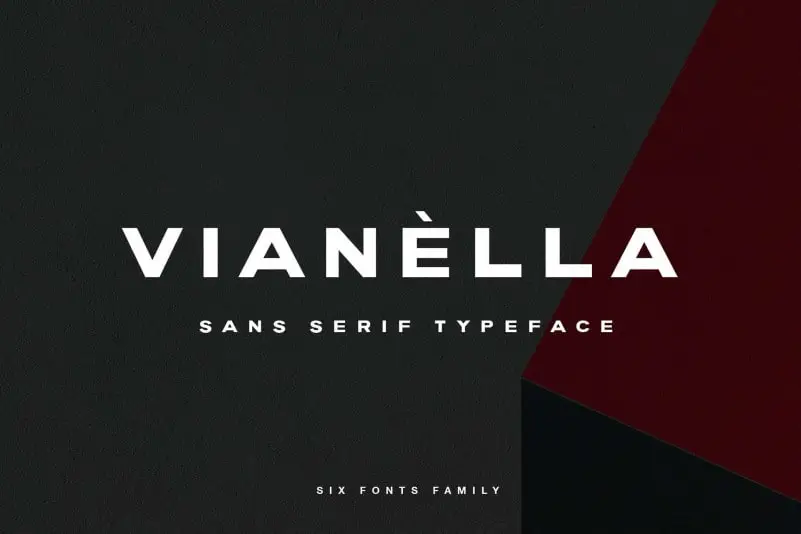
Vianella Sans Serif Font – Download Grátis
Sua Vianella Sans Serif Font é a escolha perfeita para aqueles que buscam uma tipografia casual e versátil que transmite confiança. Esta fonte sans-serif é ideal para manusear com letras grandes, adequada tanto para o texto da quote quanto para logotipos ou cabeçalhos de revistas. Suas opções de estilo vão desde o bold até a linha de baixo, garantindo um ar contemporâneo em qualquer projeto. Vianella não se prende a estereótipos: pode ser usada tanto na impressão quanto no design digital, sempre mantendo seu charme minimalista e elegante. Que tal adicionar uma pitada de personalidade à próxima peça gráfica que criará? Com certeza, sua Vianella Sans Serif Font nunca desiludirá!